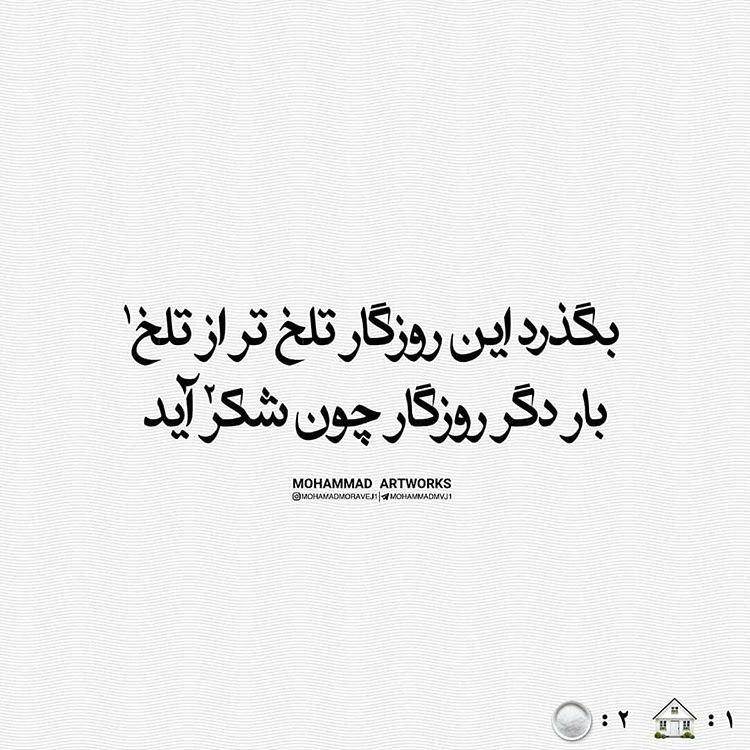
فونت اسماء
فونت اسماء - Asmae Font
فونت فارسی اسما
طراحی فونت اسماء بر اساس خطاطی دوست خوب و هنرمندم آقای حسین فاطمی در دوران همکاری با هم در گذشته های نه چندان دور استارت خورد و تا سال 1397 طراحی آن ادامه داشته است .
تعداد زیاد مرکبات این فونت به علت نمایش توازن فونت در فاصله ها این فونت را از بقیه همرده های آن متمایز نموده است .
حروف متوازن ، زیبا و در عین حال با انعطاف پذیری بالا از خصوصیات بارز این فونت می باشد .